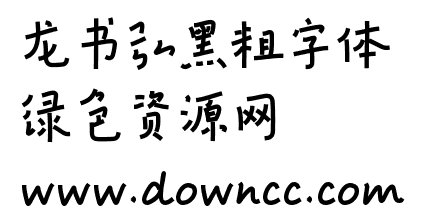
龍書弘黑粗字體是在龍書弘黑體的基礎(chǔ)上加粗修飾而來(lái),文字造型更加雄偉大氣,容易給人留下深刻印象,讓大家對(duì)標(biāo)題文字的處理更加便捷,綠色資源網(wǎng)獨(dú)家推薦!
龍書弘黑粗字體造型上十分q萌,有著童真童趣的憨厚可愛的藝術(shù)特色,字跡深顯隨意清爽的亮點(diǎn),能給人眼前一亮的視覺效果。